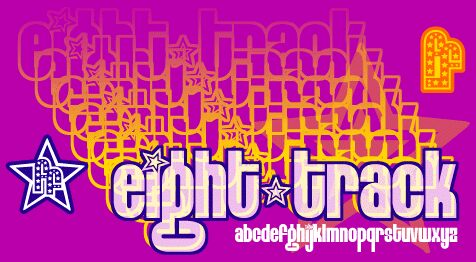
Eight Track von Font"a"licious Fonts ist eine kostenlose, groovige Display-Schrift, die direkt auf die Tanzfläche der 70er Jahre führt. Die wuchtigen, aufrechten Buchstaben mit ihrem engen, blockartigen Rhythmus wirken wie auf Vinyl-Cover gestempelt, während das verspielte Sternchen-Detail für einen Hauch von Scheinwerferlicht sorgt. Dank der fetten, einheitlichen Strichstärke wirkt sie solide und fast gummiartig – sie ist auf einen Blick laut und deutlich lesbar.
Nutzen Sie Eight Track, um Party-Poster, Retro-Musikcover, Festival-Brandings, nostalgische Logos, Social-Media-Grafiken und auffällige Merchandise-Artikel mit dem richtigen Vibe zu versehen. Diese kostenlose Schrift glänzt, wenn sie in großen Überschriften laut sein darf und durch eine klare, geometrische Sans-Serif im Kleingedruckten unterstützt wird. Halten Sie den Zeilenabstand eng, um die gestapelte, groovige Energie zu bewahren und die schweren, schwarzen Formen Ihre Farb- und Texturexperimente tragen zu lassen.